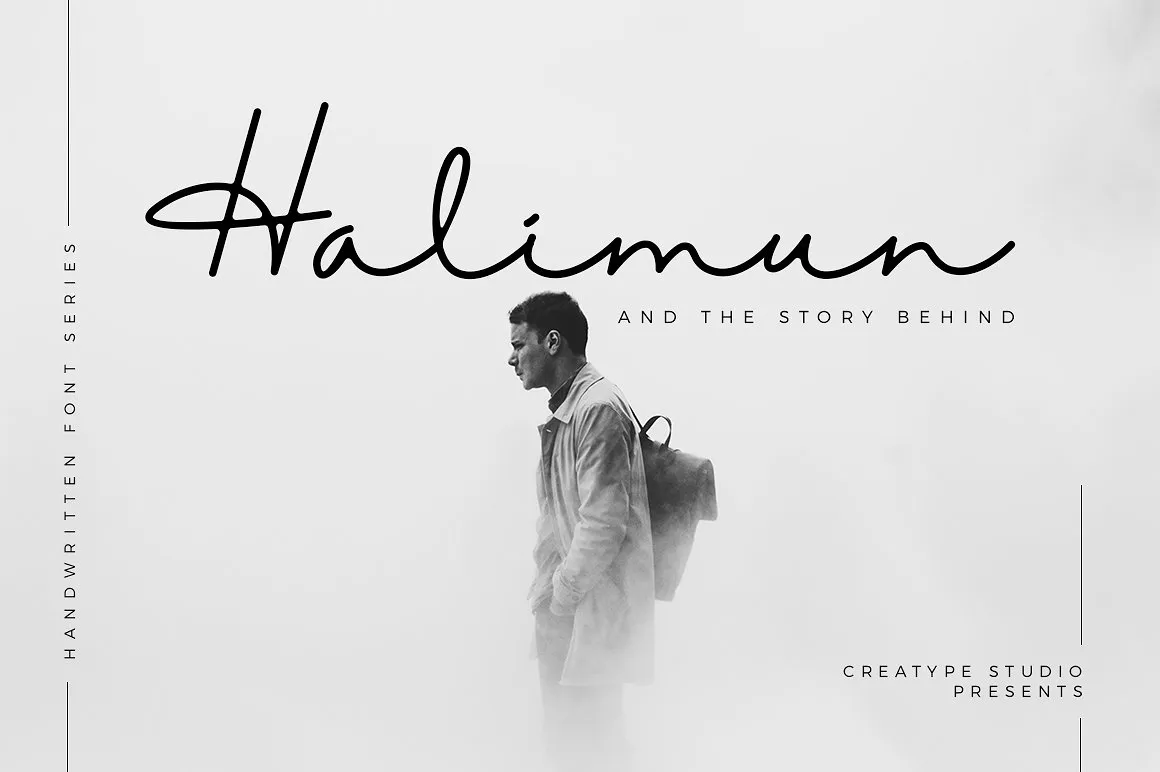
Halimun Script Style Font – Download Grátis
Bem-vindo ao mundo do design visual! Aqui está uma descrição para a fonte Halimun Script Style que você pode usar no download: Introduzimos Halimun, uma fonte escrita à mão com estilo autêntico criada pelo estúdio Creatype. Esta é uma nova opção moderna e fresca, combinando elementos de escrita à mão e estilo de fonte para criar um resultado elegante, natural e sofisticado. Halimun é perfeito tanto para projetos que precisam da sensação única do traçado manual, como fotografias, marca d’água, posts nas redes sociais, anúncios, logomarcas e branding, cartões de convite, designs de produtos, rótulos, selos, festas de casamento, embalagens de produtos especiais ou eventos especiais. Halimun é uma escolha ideal para deixar seu projeto com um toque autêntico de escrita à mão. Descubra como essa fonte pode transformar seus projetos.